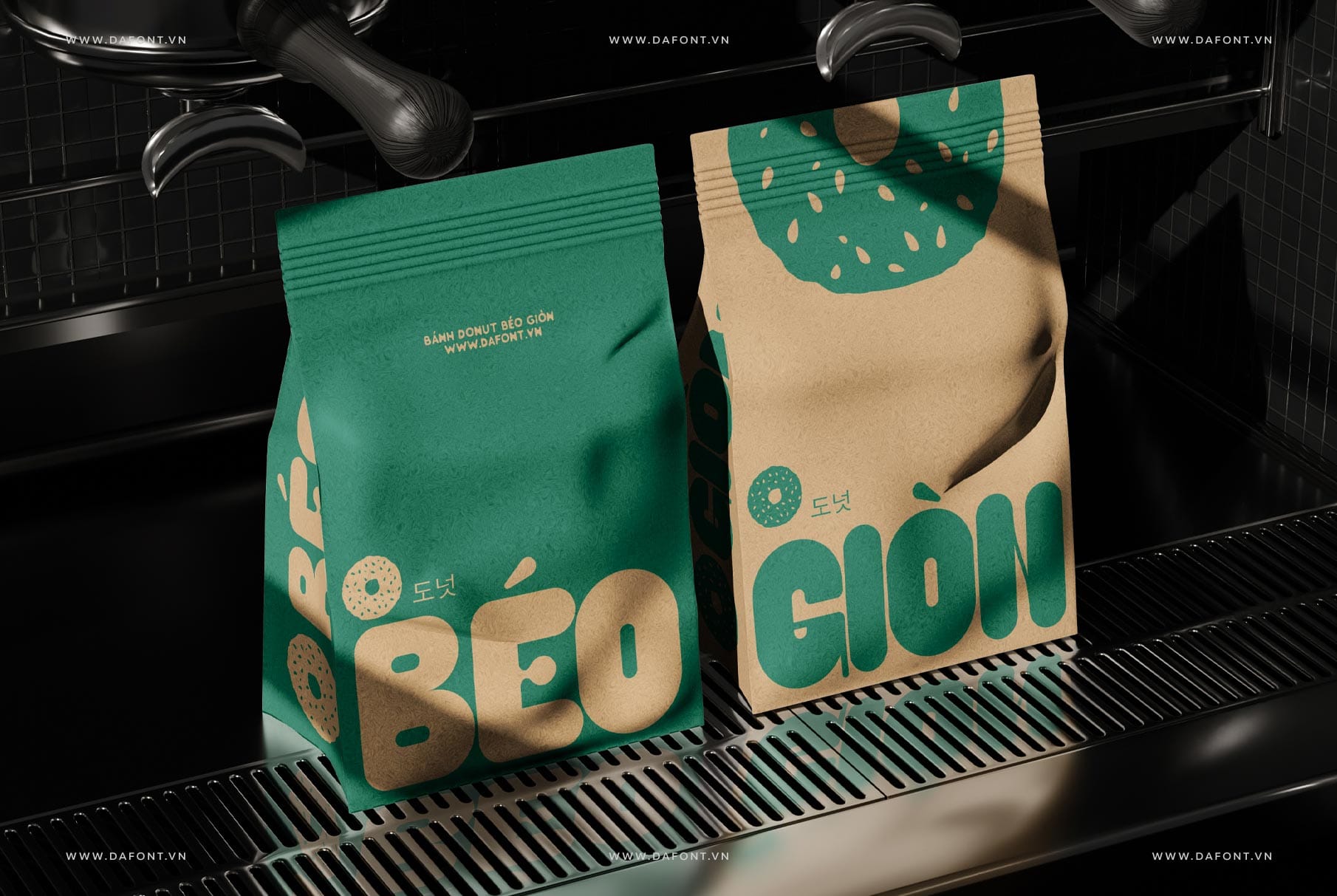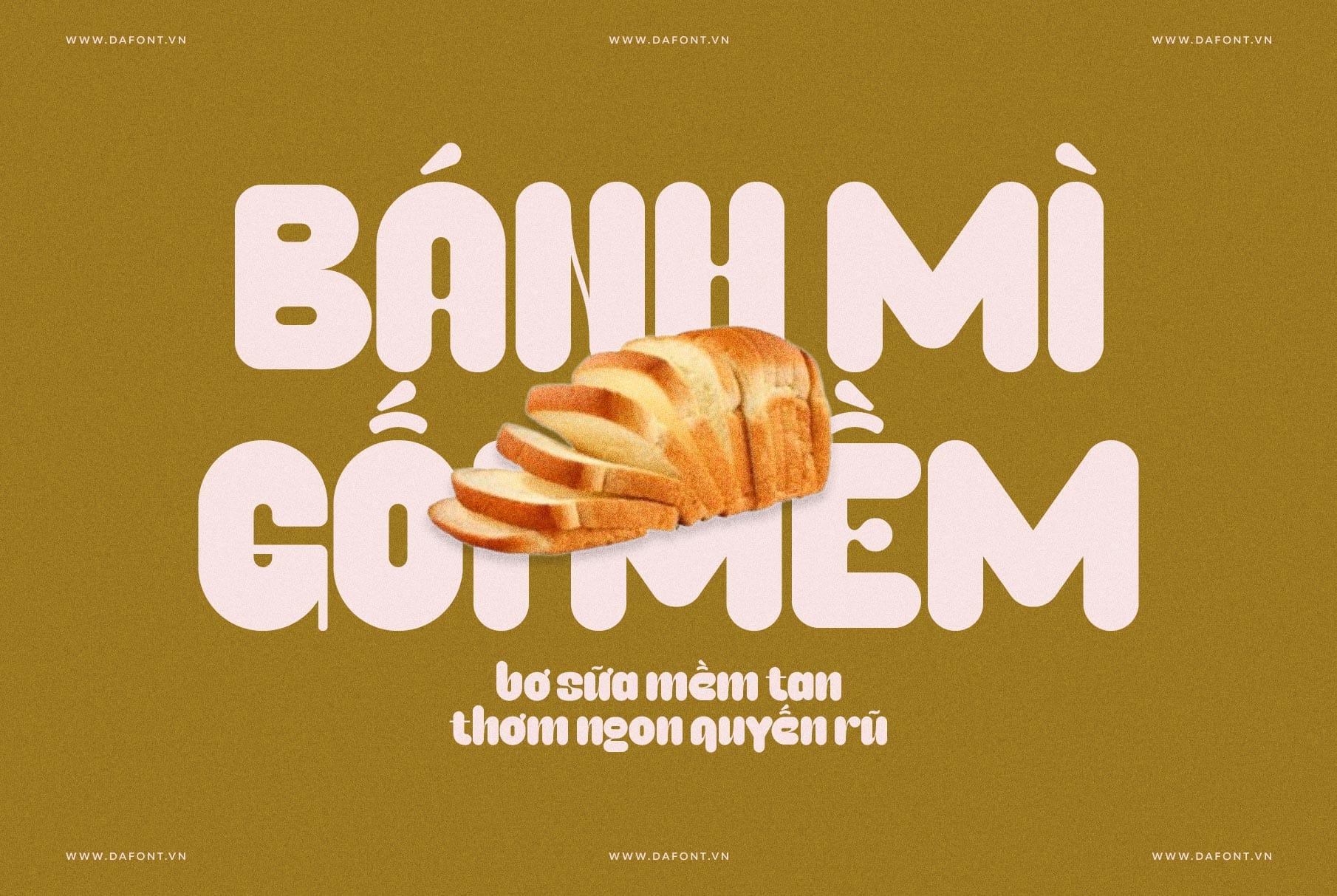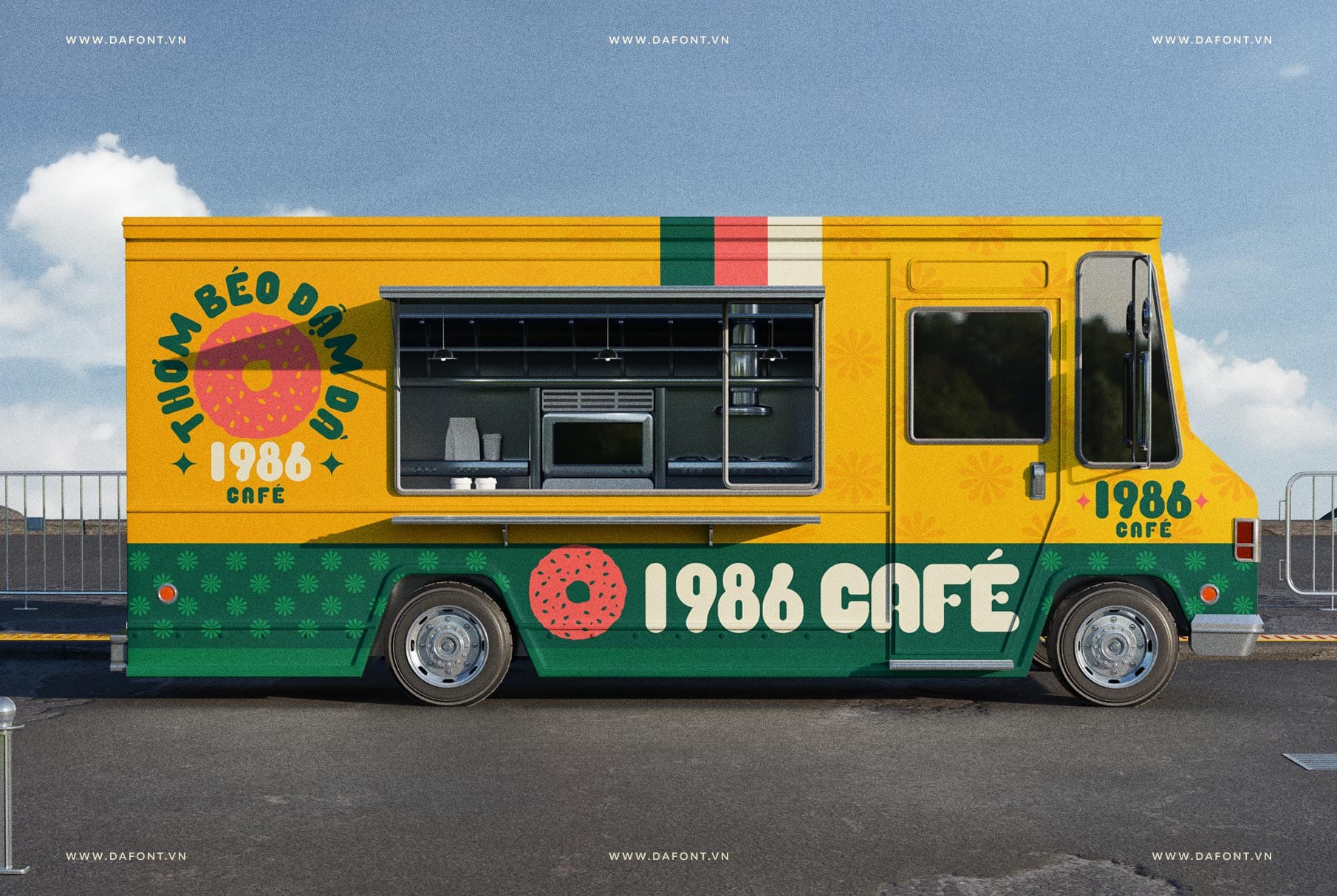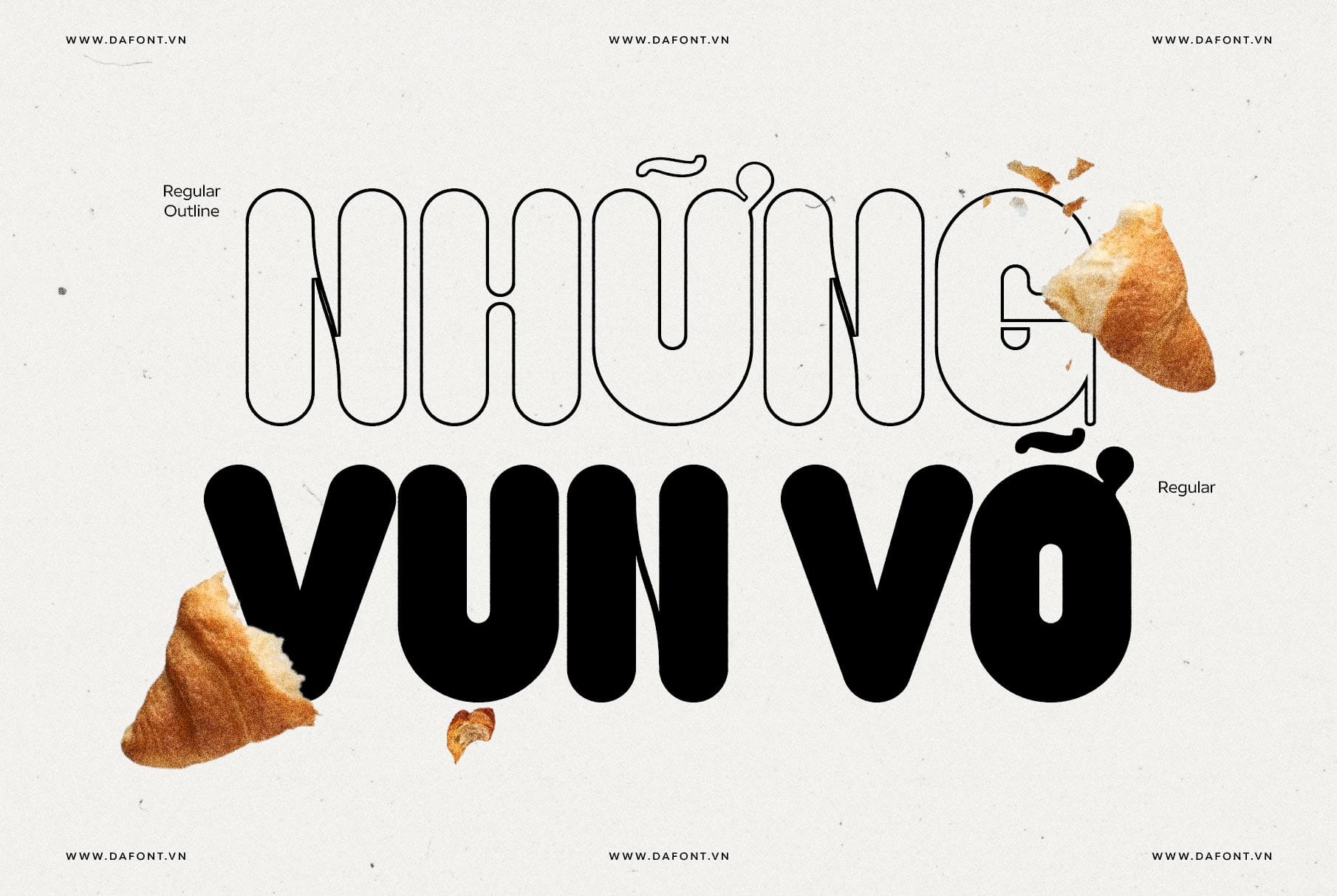
DFVN Caprifig font nổi bật với vẻ ngoài độc đáo, hiện đại và đầy cá tính. Với thiết kế tròn trịa, mềm mại nhưng không kém phần táo bạo, Caprifig là lựa chọn lý tưởng cho những ai muốn làm mới các dự án sáng tạo của mình.
DFVN Caprifig – Tròn, béo, xinh
Font Caprifig là một kiểu chữ sans-serif được thiết kế với các đường nét tròn trịa, mang phong cách hiện đại và sáng tạo. Điểm đặc biệt của font này nằm ở hai phiên bản:
- Regular: Dày dặn, chắc chắn, phù hợp cho các thiết kế cần sự mạnh mẽ và nổi bật.
- Outline: Nhẹ nhàng, thoáng đãng với các đường viền tinh tế, lý tưởng cho các dự án cần sự vui tươi và thanh thoát.
Với sự kết hợp giữa tính thẩm mỹ và cá tính riêng, Caprifig không chỉ là một font chữ mà còn là một công cụ giúp các nhà thiết kế thể hiện phong cách độc đáo của mình.
Đặc điểm nổi bật DFVN Caprifig
Caprifig là một font chữ độc đáo và ấn tượng, mang đến nhiều đặc điểm nổi bật khiến nó trở thành lựa chọn yêu thích trong các dự án thiết kế. Dưới đây là những điểm nổi bật của DFVN Caprifig:
- Vẻ đẹp độc đáo: Đường nét tròn trịa kết hợp với sự hiện đại tạo nên một Caprifig vừa gần gũi, vừa khác lạ — điều mà hiếm font chữ nào làm được.
- Tăng tính nhận diện: Sử dụng Caprifig trong logo, banner hay website giúp thương hiệu của bạn dễ dàng ghi dấu ấn trong tâm trí khách hàng.
- Dễ dàng kết hợp: Caprifig hòa hợp với mọi phong cách thiết kế, từ tối giản đến phức tạp, từ vintage đến futuristic.
- Truyền cảm hứng: Chỉ cần nhìn vào Caprifig, bạn sẽ muốn bắt tay ngay vào một dự án mới — nó khơi dậy sự sáng tạo một cách tự nhiên.
- Dấu được làm mới: Toàn bộ dấu được làm mới và tối ưu tạo nên sự hài hòa và thẩm mỹ tăng cường cho kiểu chữ.
DFVN Caprifig phù hợp cho nhiều dự án thiết kế
- Thiết kế thương hiệu: Một logo sử dụng Caprifig Regular sẽ mang lại cảm giác mạnh mẽ, chuyên nghiệp, trong khi Caprifig Outlined lại tạo nên sự trẻ trung, phóng khoáng.
- Quảng cáo và poster: Font này khiến các tiêu đề trở nên sống động, thu hút ánh nhìn ngay từ cái nhìn đầu tiên—rất lý tưởng cho các chiến dịch marketing.
- Website và UI/UX: Sử dụng Caprifig cho các nút CTA (Call-to-Action) hoặc tiêu đề phụ để tăng tỷ lệ nhấp chuột và giữ chân người dùng lâu hơn.
- Sản phẩm sáng tạo: Từ thiệp mời, bìa sách đến nhãn sản phẩm, Caprifig đều mang lại sự mới mẻ và cuốn hút.
Ví dụ thực tế: Một quán cà phê sử dụng Caprifig Outlined trên menu của mình để tạo cảm giác thân thiện, gần gũi, trong khi một thương hiệu bánh mì chọn Caprifig Regular để thể hiện sự đáng tin cậy và đổi mới.